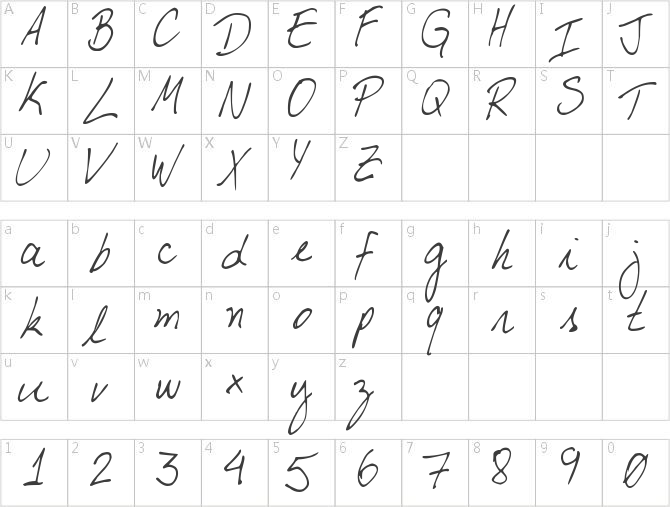
DJB My Boyfriends Handwriting
DJB My Boyfriends Handwriting介绍
DJB My Boyfriends Handwriting字体字库是一款让人赏心悦目、百看不厌的英文字体,适合各类广告和产品包装设计应用,字体大小0.06MB,格式为ttf字体,上传用户是浪遍塞纳河的,作者/版权方为未知